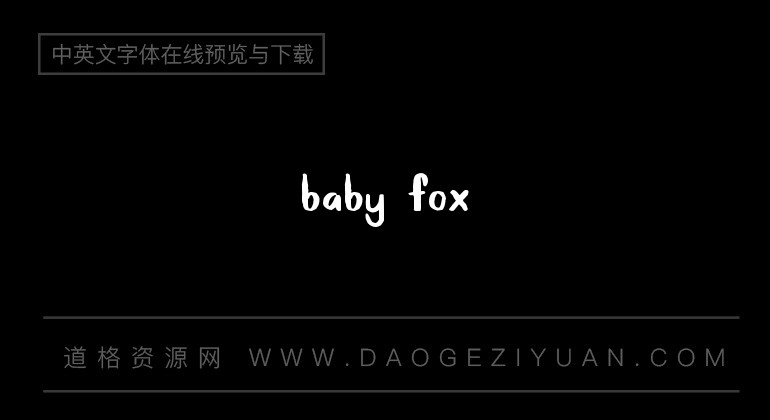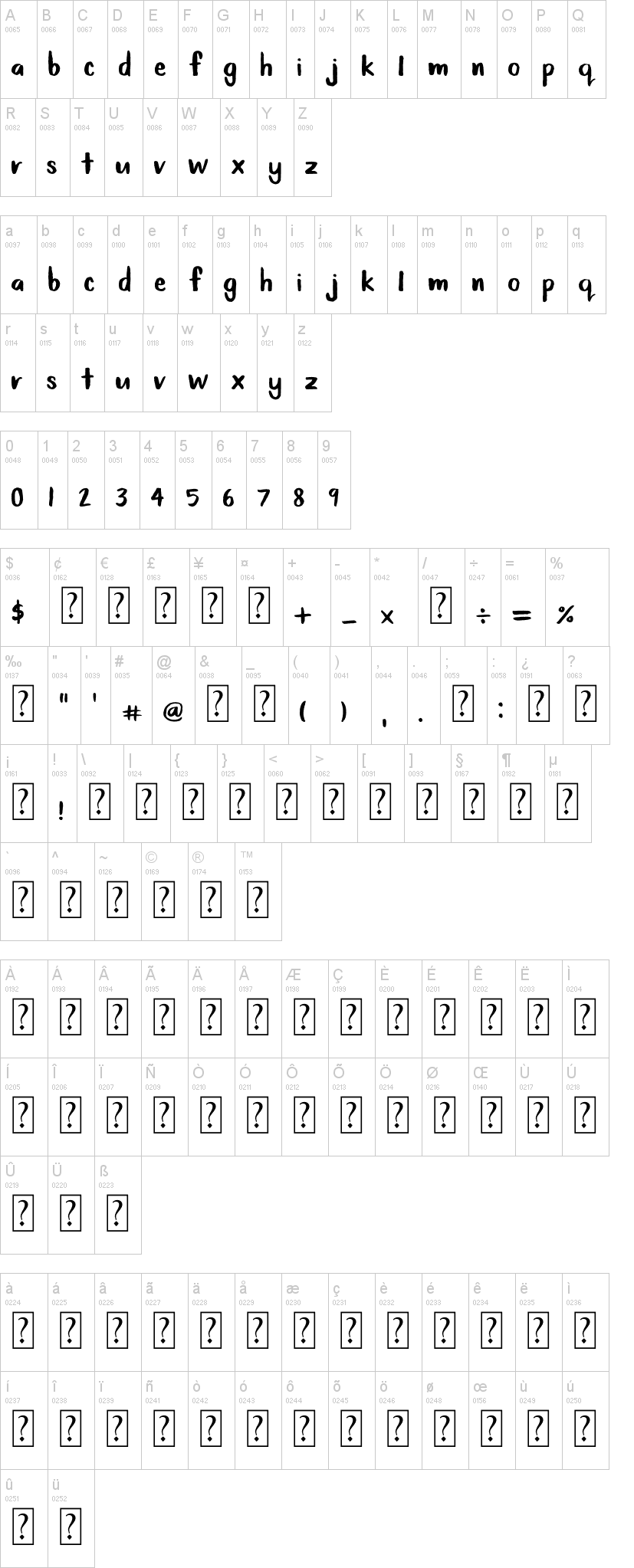
Baby Fox
Baby Fox 字体是一款极具特色的手写风格字体,它有着可爱的外观,可以营造出温馨、活泼的氛围。它的字形清晰,可以更好地表达文字的意思,而且它的行距也很宽,可以让文字更加突出显眼,更容易被读者阅读。它还有许多不同的字体大小,可以满足不同的设计要求,可以用于各种场景,从婴儿的照片到婚礼的邀请函,都能用上它。
Baby Fox是一款非常不错的手写艺术字体,具有很好的视觉感,适合于文化类的宣传设计、商业类品牌的广告和产品包装设计以及个性化文字排版等较多场景。
Baby Fox字符映射图